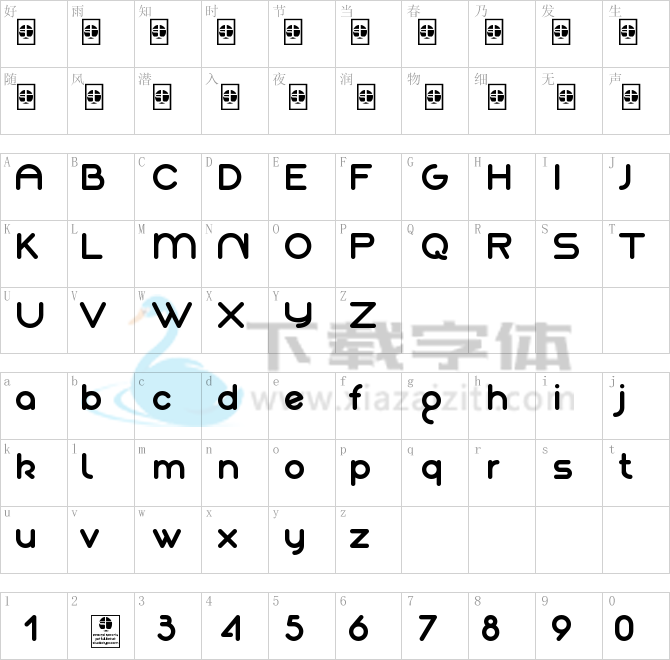
Akaju.otf字体下载,这款字体结构工整、笔画清晰,兼顾美观与易读性,适用于标题、正文、海报、包装、LOGO 等多种场景。字形优雅稳定,风格百搭耐看,适配日常排版与创意设计,让文字呈现更舒适、更具质感。Akaju.otf字体下载一笔一画,皆是细节,以均衡的比例、流畅的线条打造舒适视觉体验,字形端正大气,风格简约现代。无论是商业设计、品牌宣传还是日常排版,都能轻松驾驭,让文字更有格调与力量。Akaju.otf字体下载字体下载。
• 字体名称:Akaju